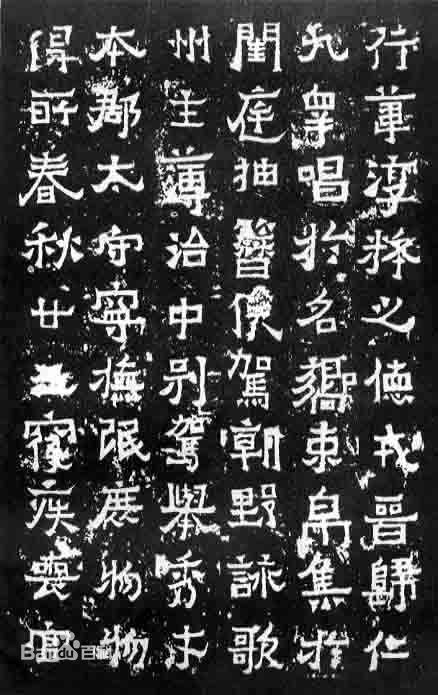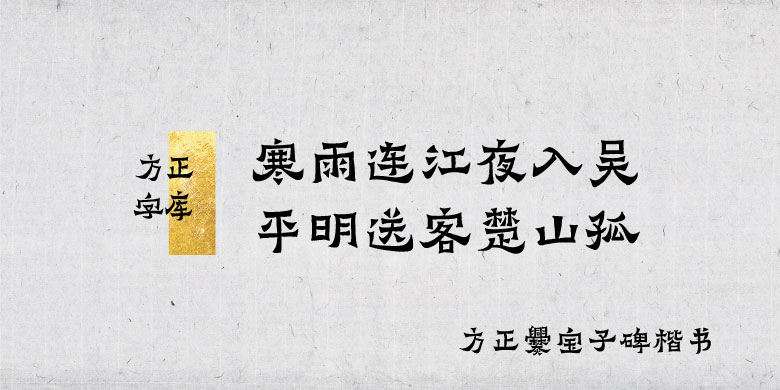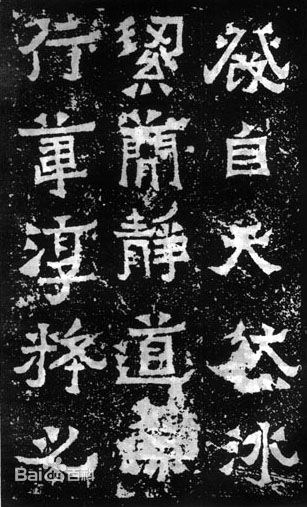
方正爨宝子碑楷书
设计师: 苏新诗,汪文
字体介绍:
爨宝子碑 东晋碑刻,正书,碑额题“晋故振威将军建宁太守爨府君之墓”。义熙元年(公元405 年,此时已改年号为义煕,或因边陲闭塞,故书碑人仍依旧年号写作“大亨四年”)立。清乾隆四十三年(1778 年)在云南曲靖南七十里扬旗田出土,道光十五年(1835 年)《云南通志》始著录,咸丰时移置城中武侯祠。书体在隶楷之间,可见文字由隶书演变为正书过程中的一种风格。
字体特征:以《爨宝子碑》为字形开发依据。朴茂古厚,大巧若拙,率真硬朗,气魄雄强,奇姿尽现,浑然天成。体势情趣、情态均在隶楷之间。
国博文物:爨宝子墓碑拓片
爨宝子,建宁同乐 (今云南陆良)人。生于公元380年,卒于公元403年,年仅23岁。他19岁时即“弱冠称仁”,就任建宁(今云南曲靖)太守。当时,正是爨氏统治南中的强盛时期。
《爨宝子碑》 ,全称《晋故振威将军建宁太守爨宝子碑》,东晋义熙元年(405年)立,清乾隆四十三年(1778年)出土于云南曲靖县南杨旗田,今存曲靖县一中校园内。碑高5尺4寸,宽1尺8寸。碑额书“晋振威将军建宁太守爨府君之墓”15字;正文13行,满行30字,共336字,字径约1寸;下列题名13行,行4字。碑额、正文、题名均为正书,前后风格一致,体在楷、隶之间。正文末行“立”字下刻有清咸丰二年(1852年)曲靖知府邓尔恒隶书跋六行。跋云:“考晋安帝元兴元年壬寅改元大亨,次年仍称元兴二年,乙巳改义熙。碑称‘大亨四年’,殆不知大亨年号未行,故仍遵用之耳。”邓说不虚,“大亨四年”实为义熙元年。旧拓本无邓跋。
《爨宝子碑》的出土地云南,在东晋属“南中”之地,所居少数民族被称为“西南夷”。与中原和江南相比,此地经济文化相对落后,是当年的僻邑荒郡。宝子一族即为当地土著,且为大姓。其祖辈有史可稽者可追溯到爨习,他是诸葛亮南征时所降服的南中俊杰之一,事蜀后,官至领军。其后相继有爨肃仕于曹魏,爨云仕于北魏,宝子则仕东晋,且官至“建宁太守”,可见,爨氏虽为蛮族,但由于与汉政权保持着密切的联系,从蜀汉之际始,便接受汉文化的薰染。而且,宝子所辖之地在汉代曾一度成为中国西南边陲的国际交通要道,是中外交通东西往来的必经之地。与内地频繁的交往,中土的文化必然通过各种渠道传至南中,其中包括文字与书法。因此,俨然汉制的《爨宝子碑》出现在南中,初看令人匪夷所思,颇生诧异,但从其历史地理背景加以考察,却在情理之中。
魏晋是书法史上新旧书风的转换期,主要是隶书向楷书和行书转换。这里只谈隶楷之变。在“变”的强风吹刮下,新旧书体的点画和形态均呈现出新的面貌:一方面,旧体的隶书旧得不地道常有楷书的写法;另一方面,新体的楷书新得不完善,时见隶书的影子。因此,新旧杂糅,楷隶相参,是这一时期时代书风的显著特点。只不过因年代的先后和实用目的及书者书艺的不同,具体到作品中,楷隶之间的比重有异而己。有的以隶为体,参以楷法,隶多于楷;有的以楷为体,留有隶意,楷多于隶;有的则楷隶参半,实难定其为楷书或者隶书,《爨宝子碑》便是典型。只因康有为在《广艺舟双楫》中称此碑为隶书,以后的著述皆沿用此说。其实,我以为这未必很恰当。但既已约定俗成,也只好如此了。
那么,《爨宝子碑》为何会出现这种非楷非隶,亦楷亦隶,楷隶参半的面貌呢?裘锡圭先生在《文字学概论》中说,该碑作者“想模仿八分而又学不像,字体显得很不自然”,我觉得很有道理。
我们知道,在汉字书法发展史上,手写体墨书和刻铸铭文是相对独立,自成系统的,同时又相互影响,彼此制约。从时间上看,手写体墨书总要比刻铸铭文转化得早一些。春秋战国时,篆书向隶书的演变是这样,魏晋之际隶书向楷书的演变同样如此。之所以有这种差异,主要是不同的实用目的造成的。手写体墨书多用于日用文书、簿籍之类,因求简便,在赴速急就的书写过程中,用笔往往草化,并使用俗笔,从而解散旧体,产生新法。开始是少数人,后来使用的人渐多,并加以规范定型,便成新体。魏晋时,经钟繇到二王,楷书已经成熟,即新体已成,并广泛地运用于官府文书和日常生活之中,流风波及南中。虽难见实物资料,但可以推断,《爨宝子碑》前后,南中的手写体墨书当与中原、江南相仿佛,即与魏晋写经、敦煌写经以及钟王一脉书迹相似而后可。即使由于南中地处边陲,通讯远阻,其新体楷书不如中土成熟,但也不至于相差太远。也就是说,在当时的南中,楷书(即使尚存隶意)已是社会各层在日用生活中的通用字体。因此,《爨宝子碑》的作者能作楷书是毫无疑问的。
刻铸铭文则不同,它的主要目的是实用,或是门生故吏为其府主立碑或是子孙后嗣为其祖辈伐石,既欲昭示于众,又望传之久远。因此,为表其敬意,示其庄重,多采用古体字。这是中华民族由长期积淀而成的崇古意识在汉字书法上的反映。故尽管当时楷书新体书风炽烈,此碑却仍沿续汉代以来的传统以隶书作为正规书体。刻铸铭文在字体选择上的保守性,便约束了它向新体转换的速度,而总要比手写体墨书慢一拍。而且《爨宝子碑》前后,旧体隶书既已不再是公私往来文书的通用字体,习者日少,隶法渐趋衰微,故《爨宝子碑》的作者不善隶书,亦不言自明。
因此,《爨宝子碑》的作者以楷书新体之法强为旧体隶书之体,只能状其仿佛,其结果便是不伦不类,非楷非隶,处于一种“两不像”的尴尬境地,字体也就显得很不自然了。当今不谙隶法的学书者开始写隶书时,也往往以楷入隶,字形与此相类。但又有本质的不同;前者在“两不像”的尴尬中蕴含着深沉的艺术魅力,能给人以无限的美感,而后者却是实实在在的不伦不类,除了以楷、隶拼合而成的字形外,别无他物。这种在审美上悬隔千里的差别,是由于历史、哲学、民族、心理造成的,抑或是其它?个中原委,发人深思。
《爨宝子碑》的作者不善隶法而勉强为之,方书之时,一方面怀肃穆之情,慎重为之,一方面功力不济,手不由心,结果事与愿违,欲求工而愈不工。这样便出现了许多不合常法甚至“毫无道理”的用笔和结体。这些不合情理的用笔和结体便构成了该碑最显著的艺术特征——奇姿异态。如果一切都应规入矩,一切都如应该的那样,则何奇之有,何异存焉?
先看点画。该碑大多数点画是楷与隶的复合体。众所周知,隶书最典型的用笔是波挑,其形态以蚕头雁尾为特征。该碑大部分波画、挑画的收笔与汉隶没有多少区别,但起笔却用楷法,改逆入为切入,变蚕头形成斜方形。这样,波画便成为该碑最具特色的点画:中间平两头翘,俨如一叶小舟。竖撇的起笔亦顺锋斜切,是楷书的写法,而有的撇画则全用楷法,如“吏”、“咸”、“仪”等。钩画有的像隶书,有的像楷书。点也很有特色,均为三角形,但形态、大小、方向、取势多有不同。一些短撇和短竖也写成了三角形,如“集”、“乐”。横、竖、点多为方笔,撇、捺、钩多取圆势。楷隶相参,点画变化丰富,方圆互用,厚重中增加了一些灵动之姿。另值得一提的是,该碑点画中方折锋利的棱角,用毛笔是写不出来的。而是参合了刻手随意发挥的成分,是刻手在书丹原迹基础上强化的结果。
二看结体。总体而言,该碑尚具隶书的特征:横平竖直,以保持重心的平稳;撇、捺、长横、戈钩向左右两边伸展,以求横张之势。但远不如汉隶均匀规整,即使在汉隶家族中奇崛一类的作品如《鲜于璜碑》、《张迁碑》、《封龙山颂》等,在《爨宝子碑》面前也显得保守。尤其值得在意的是,该碑有不少字打破了“雁不双飞”的基本原则,而是反其道而行之,横画和捺画的收笔同时作波状,偏来一个“双雁齐飞”,如“得”、“所”、“其”、“吐”、“芳”等不胜枚举,有的则是“三飞”甚至“四飞”,如“海”、“疾”、“庭”、“春”等。撇画也有同时向左下长长掠出的,如“沧”字。而有些横画,特别是左右结构的字左边部分的横画,按隶书常法是不能作波状的,但该碑却写成波画,如“朝”、“野”、“穆”等。此外,该碑结体时,在穿插、避让、聚合关系上也大异常法,极尽变化之能事。总之,《爨宝子碑》在结体上所表现出来的叛逆性格,使人不能不刮目相看。
楷隶互参的用笔,不拘常规的结体,以及由于字形大小参差而形成的整齐中寓错落的章法,这些外在的形式特征共同构建了《爨宝子碑》内在的艺术风格:古拙、肃穆、天真,同时又带有几分滑稽和幽默。如果打一个比喻的话,它颇像一个老顽童,既骨老血浓,又童心未眠,时有天真烂漫之举;或者说,它像一个小大人,走路尚步履蹒跚,却又故作深沉之貌,其言其行,实令人忍俊不浚因此,它是一个多种成分复合而成的综合体,但这种复合却十分自然,各种矛盾对立的因素在豪爽强悍、朴野率真的“蛮夷”“书家”笔下得到了和谐的统一。从不同的角度,在不同的心态下观赏此碑,都会有新的感受。不可否认,该碑作者的书艺是拙陋的,至少是不精隶法。但更不可否认,该碑是奇妙的,奇妙得令人心醉,令人流连忘返。而且,其拙陋处正是该碑的奇妙处,也是最能打动人心的地方。从拙陋到奇妙,是什么因素促成了这两极之间的转换,是审美观念吗?我不得而知,我只知道刘熙载“怪石以丑为美,丑到了极处也就美到了极处”的理论在这里得到了具体的落实和验证,而对《爨宝子碑》,不由自主地便思接千载以上,视通万里之遥,回望起一千五百多年以前,西南边陲少数民族那一段扑朔迷离的历史,情有所动,心亦摇焉。
说不完,道不尽的《爨宝子》!
因该碑变化太多,法无常定,初习书法者不宜学。但当有一定基础之后临习此碑,则可医涪滑、雹媚、俗诸玻临习此碑,最须注意的是要透过表象明其内理。我们知道,碑刻都有刻工自我发挥的一面,加以风雨剥蚀,已与书丹原迹有一定的出入。具体到此碑的方笔,固然书丹原迹已定其根本,刻工在此基础上把“方”作了进一步的强化,也是毫无疑问的。因此,我们在临习时,切不可以描填之法画成其方,而应遵循用笔之理得其方意。清末民初书家经亨颐先生写《爨宝子碑》不拘泥于一点一画之细枝末叶,而是从大处着手写其古拙厚重之意,却神气活现,既存有原碑凝重的金石味,又注入了清雅的书卷气,此可谓善学者。若不加分析,依样画葫芦,以柔软之毫翰拟锋利之钢刀,外摹其形,内迷其理,则终难有所获。我的导师徐利明先生在谈到临摹和创作之法时强调:应从精神入手去把握形式特征,从内理着眼去分析点画用笔,若是碑,则要透过刀锋看笔锋,化刀法为笔法,只有这样才能形神俱得,把碑写活写雅。我想,这对于临习《爨宝子碑》的朋友亦有助益。